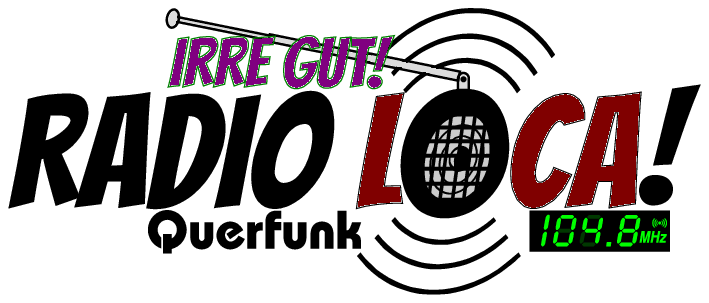
Ich suche eine Schrift mit digitalen Zahlen für ein Display
ich muss auf die Schnelle Zahlen in einem Taschenrechner-Display setzen – fällt Euch spontan ein Font mit diesen typischen Digitalzahlen ein? Ich stehe auf dem Schlauch … :oops:
Ich habe Deine Frage als sehr schwammig und unpräzise empfunden. Nur mal so, zum nachträglichen, besseren Verständnis. Was für eine Anzeige ha(te)st Du im Sinn?
• Eine 7-Segmentanzeige zur Darstellung von Zahlen (und wenigen vorgegebenen) Buchstaben, wie bei den ersten Generationen von Taschenrechnern? Das wirkt sehr rustikal, ist aber eingeschränkt bzgl. der darstellbaren Zeichen.
• Eine LCD-Dot-Matrix mit der man auch Buchstaben darstellen kann, wie sie später in programmierbaren Taschenrechnern verbaut wurden? Das ist flexibler bzgl. der Darstellung von Zeichen, wirkt aber „geleckter“.
Was waren die Anforderungen, Vorgaben und was für eine Schrift hast Du gwählt?
Ich habe mir für ähnliche Zwecke eine SVG-Grafik einer 7-Segmentanzeige für die Frequenz plus Anzeigefelder für MHz in Helvetica und den Status Stereo (((·))) für einen UKW-Tuner gebastelt und dann die Segmente manuell eingeschaltet.
Das geht auch für Taschenrechner. 😍Casio FX 100😍 aus den 1980ern.
Zu Deiner Frage: Da ich weder mit den Begriff „7-Segmentanzeige“ noch mit „LCD-Dot-Matrix“ etwas anfangen kann, hätte ich meine Frage diesbezüglich nicht spezifizieren können,  sondern habe das, was ich suche, so gut beschrieben, wie es mir eben möglich war.